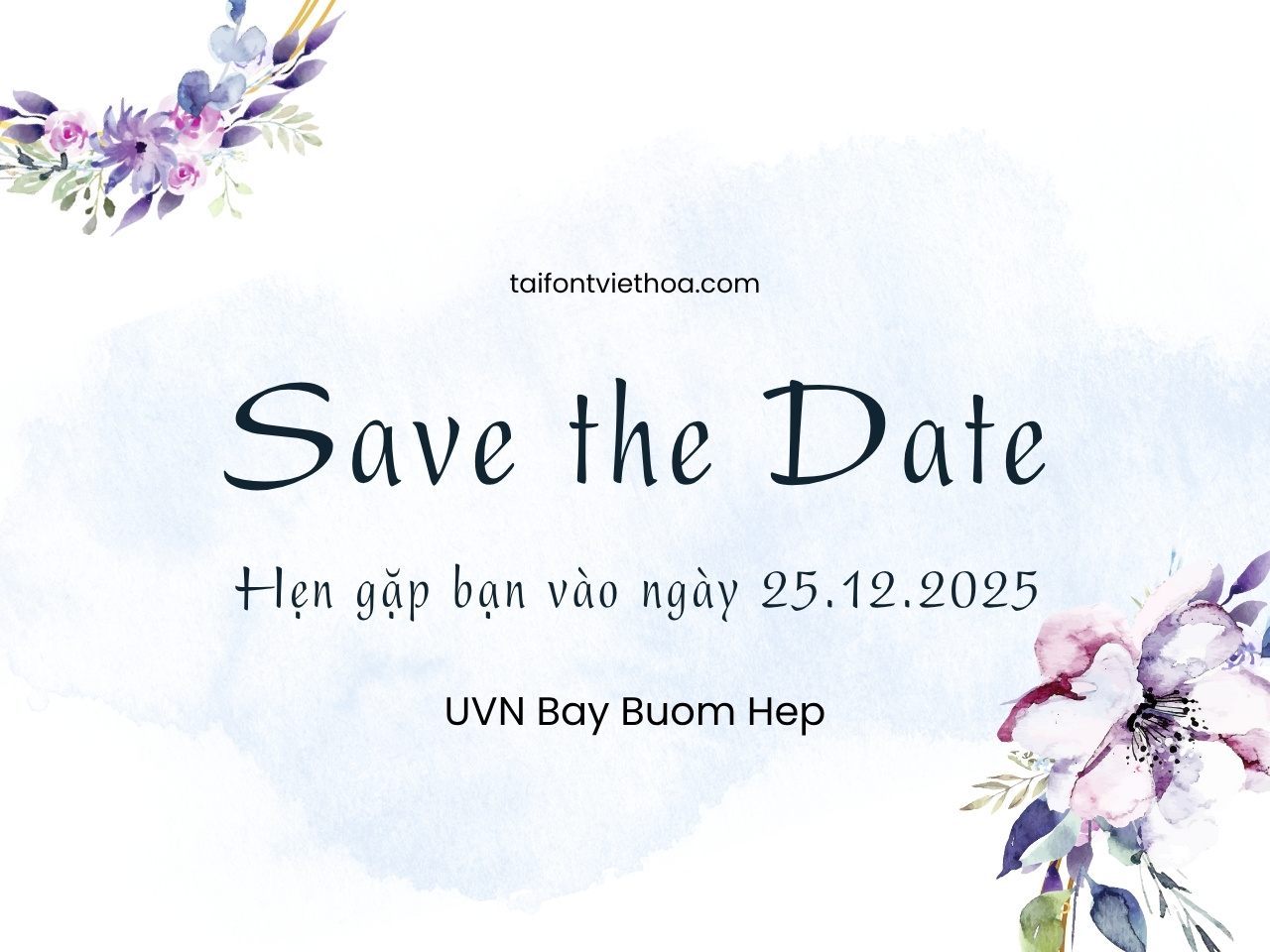
Font việt hóa UVN Bay Buom Hep
Giới thiệu về font UVN Bay Buom Hep
UVN Bay Buom Hep là phiên bản thanh mảnh, tinh tế hơn của bộ font UVN Bay Buom, mang đậm hơi thở nghệ thuật và nét đẹp mềm mại của chữ viết tay. Với cảm hứng từ hình ảnh cánh bướm bay lượn, font thể hiện sự nhẹ nhàng, nữ tính và sáng tạo. Font được sưu tầm và chia sẻ bởi thành viên Font Chuẩn, đồng thời đã được taifontviethoa.com chọn lọc, kiểm duyệt và ứng dụng vào nhiều dự án thiết kế mang đậm tính cá nhân và cảm xúc như thiệp mời, typography sáng tạo và ấn phẩm truyền thông lãng mạn.
Đặc điểm thiết kế và ứng dụng của UVN Bay Buom Hep
Với các đường nét mảnh mai, cấu trúc chữ bay bổng và khoảng cách ký tự hợp lý, font UVN Bay Buom Hep mang lại cảm giác nhẹ tênh, tinh tế và thanh lịch. Nét chữ nghiêng nhẹ kết hợp độ mảnh ổn định giúp font giữ được sự rõ ràng mà vẫn đầy nghệ thuật. Đây là lựa chọn lý tưởng cho các thiết kế cần tạo cảm giác thơ mộng, sang trọng hoặc nữ tính.
Font phù hợp với nhiều ứng dụng như: thư mời, thiệp cưới, poster nghệ thuật, logo thương hiệu cao cấp, bao bì mỹ phẩm thủ công, hoặc sản phẩm cá nhân hóa. Ngành nghề lý tưởng: mỹ phẩm, thời trang, sự kiện, thiết kế cưới hỏi, đồ thủ công, và nghệ thuật cảm xúc.